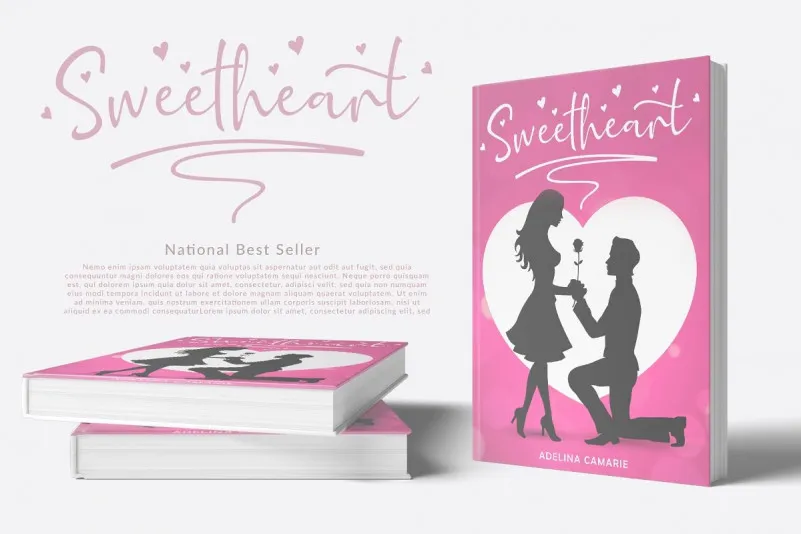
Adinda Melia Script Font – Fonte Grátis
Adinda Melia Script Font
Descubra Adinda Melia Script Font, uma moderna tipografia calligrafica para designers apaixonados por letras femininas ou projetos que exigem uma toque de autenticidade. Esta fonte é ideal para criação de logotipos de estúdios de fotografia ou convites de casamento, com suas belas linhas fluidas e características elegantes. Adinda Melia Script traz um pouco do estilo da escrita manual, criando uma aparência verdadeiramente autêntica. Com sua ampla gama de letras maiusculas e minusculas, numerais e sinais de pontuação, esta fonte oferece toda a beleza dos traços feitos à mão. Além disso, todas as minúsculas incluem opondo curvaturas que começam e terminam de forma natural, proporcionando um estilo autêntico de escrita. Com Adinda Melia Script, você pode criar uma identidade visual única para suas criações ou personalizar sua marca com um toque sofisticado e elegante. Não hesite em experimentar esta fonte moderna e envolvente que combina a perfeição da calligrafia moderna com o charme de uma escrita manual cuidadosamente desenhada.